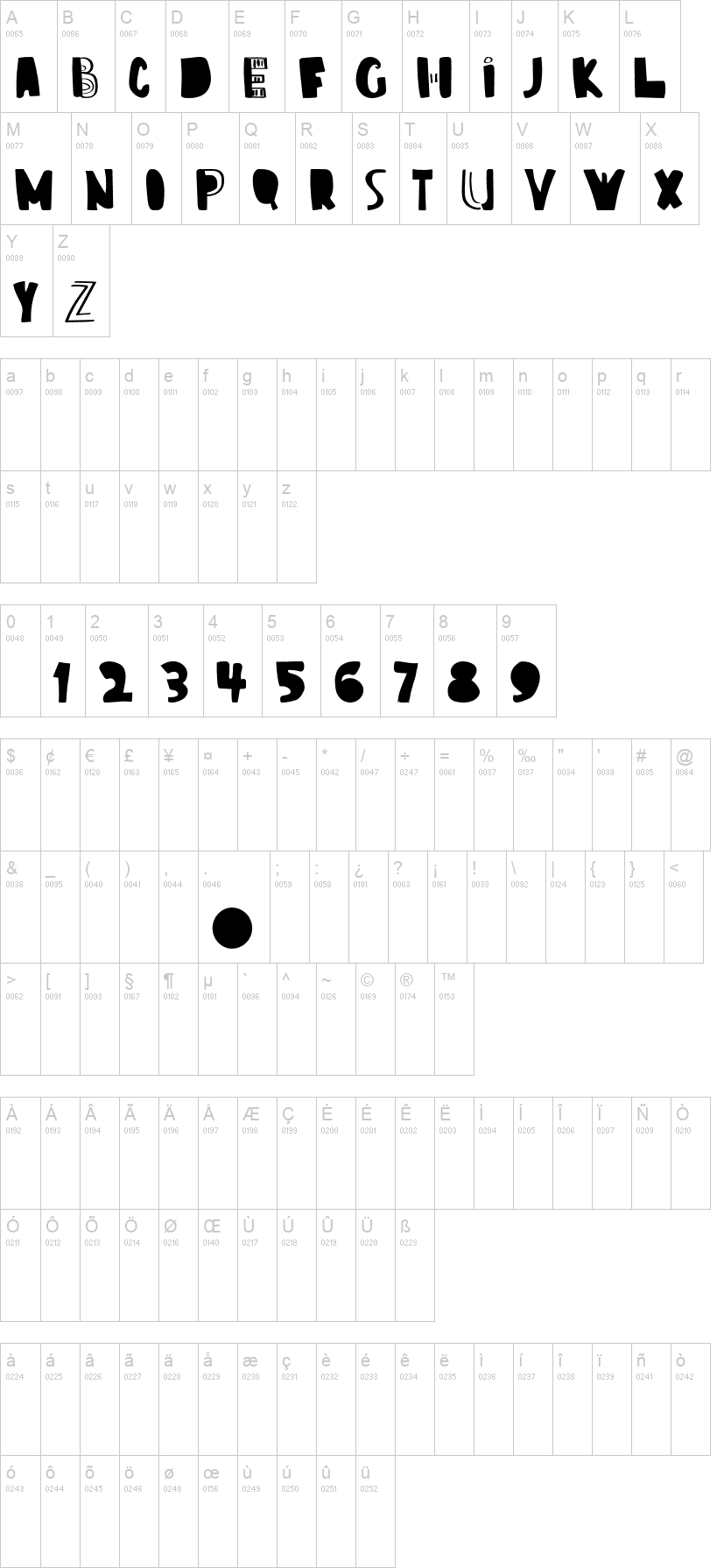
Note of the authorBelf es una letra diseñada para diseños infantiles con tendencia a lo divertido y abstracto, contiene elementos diferentes con los que podras complementar tu creatividad.